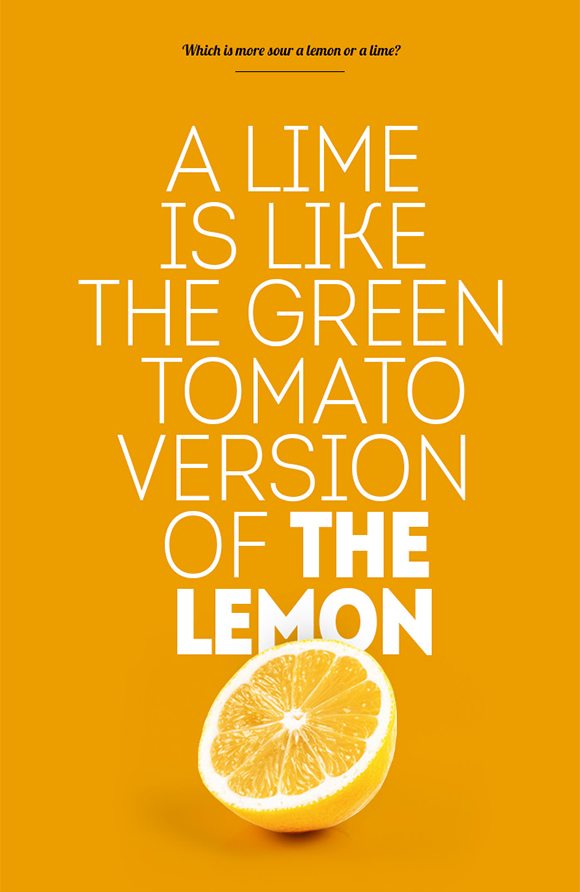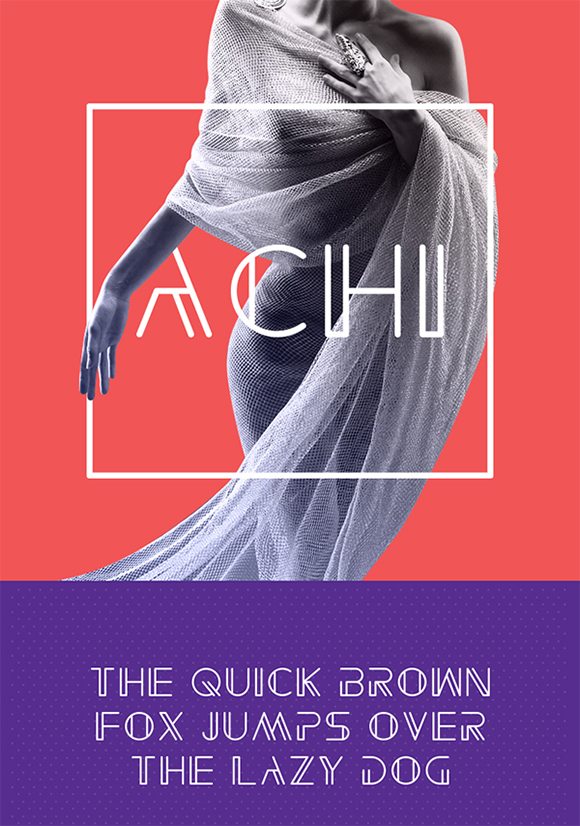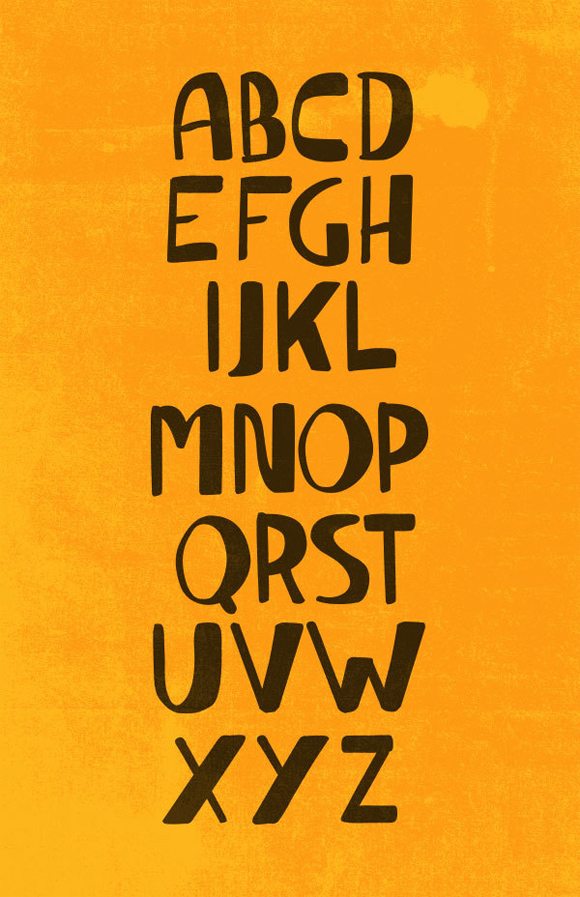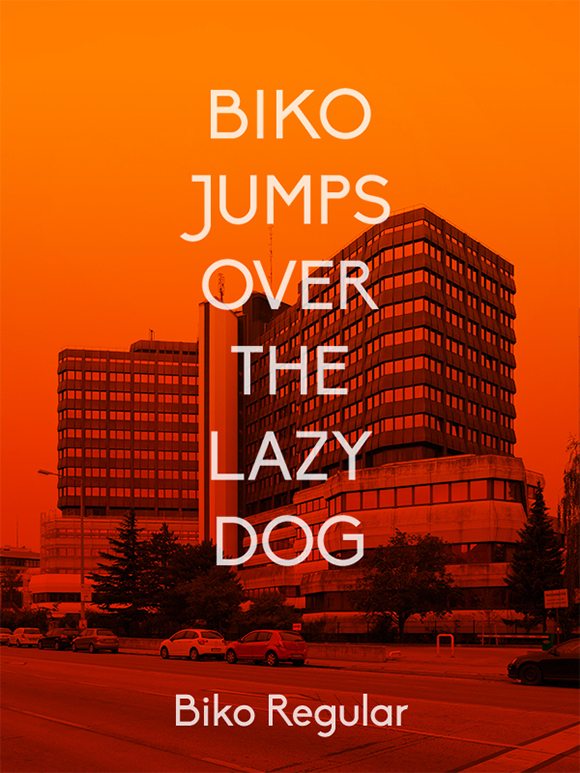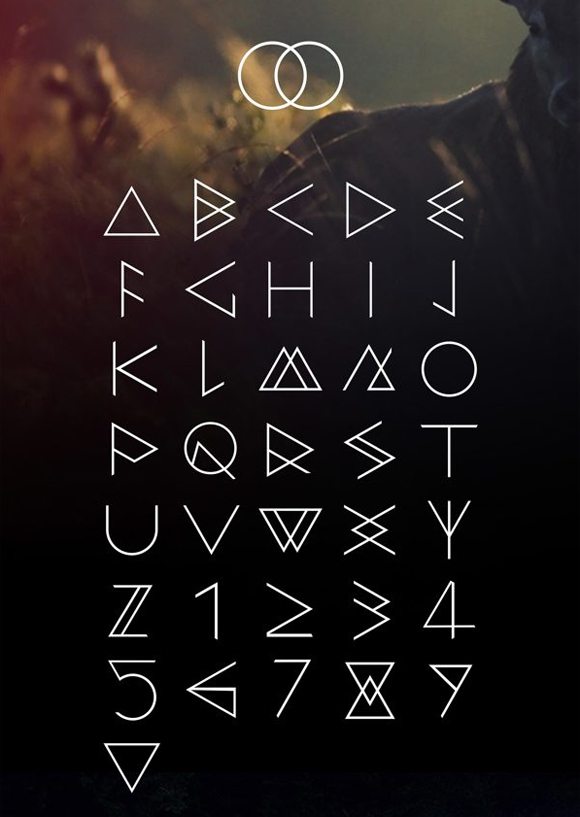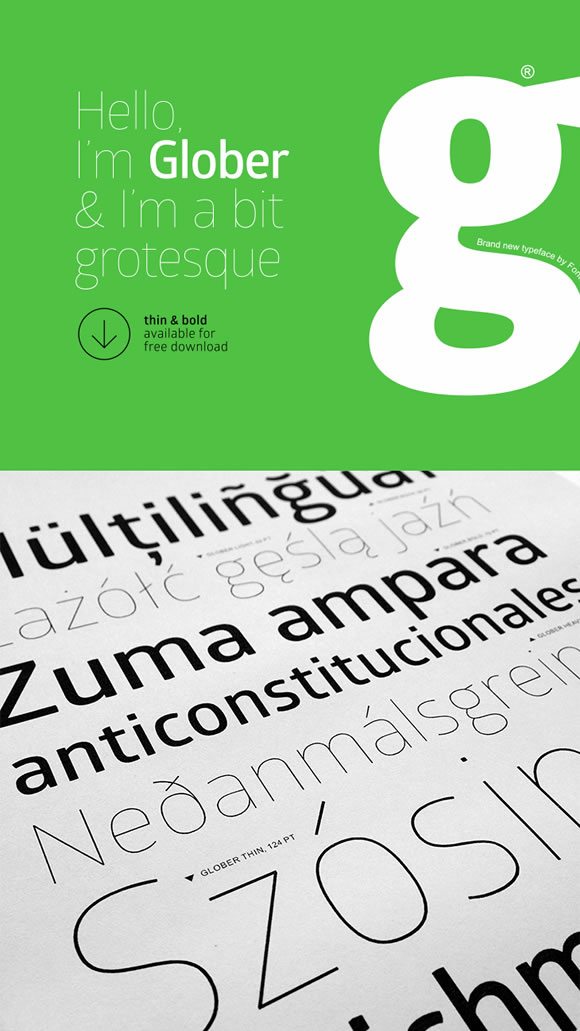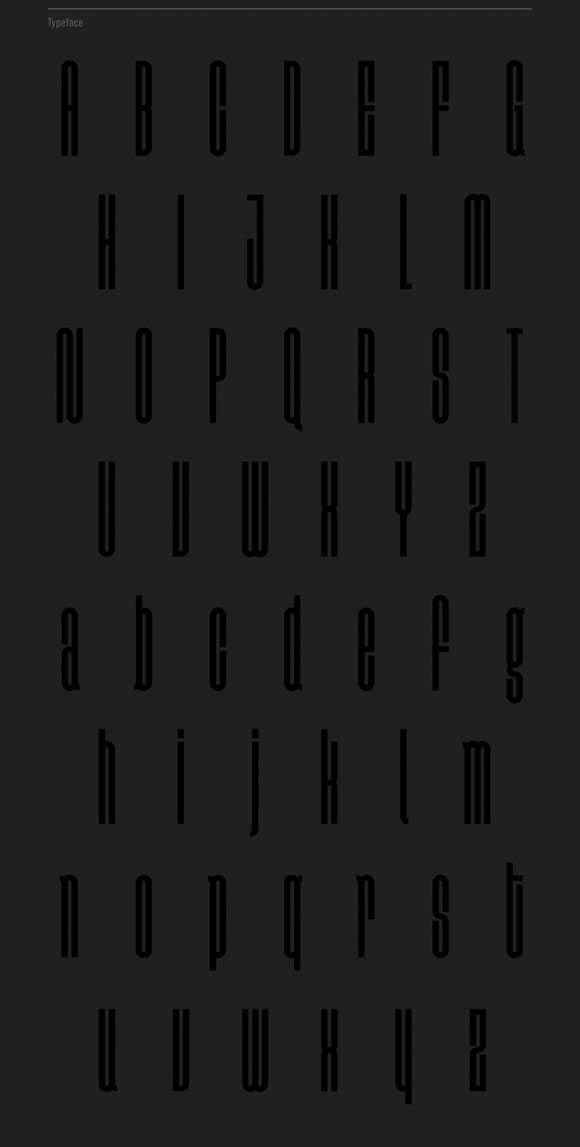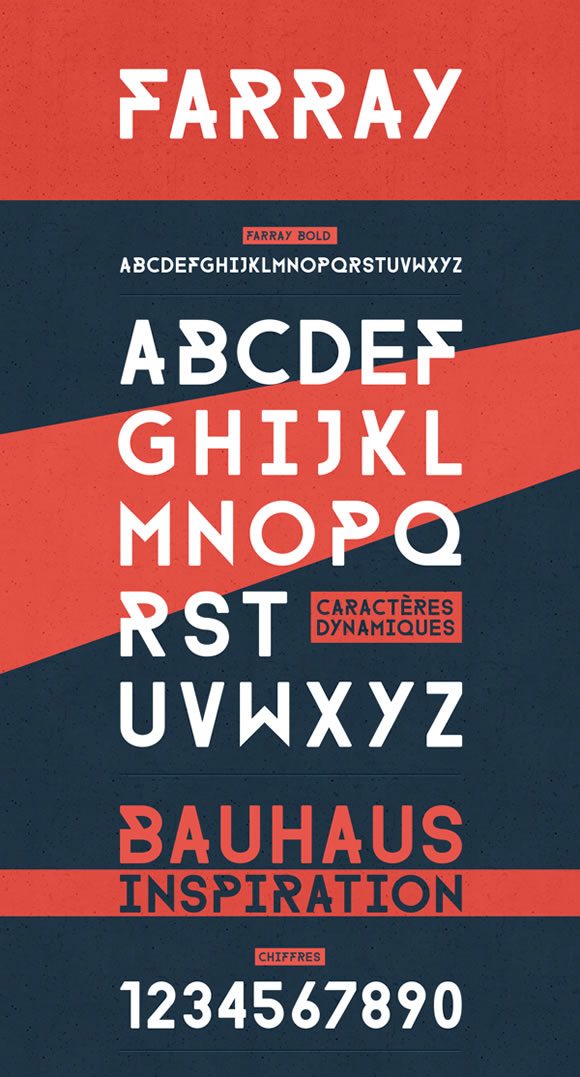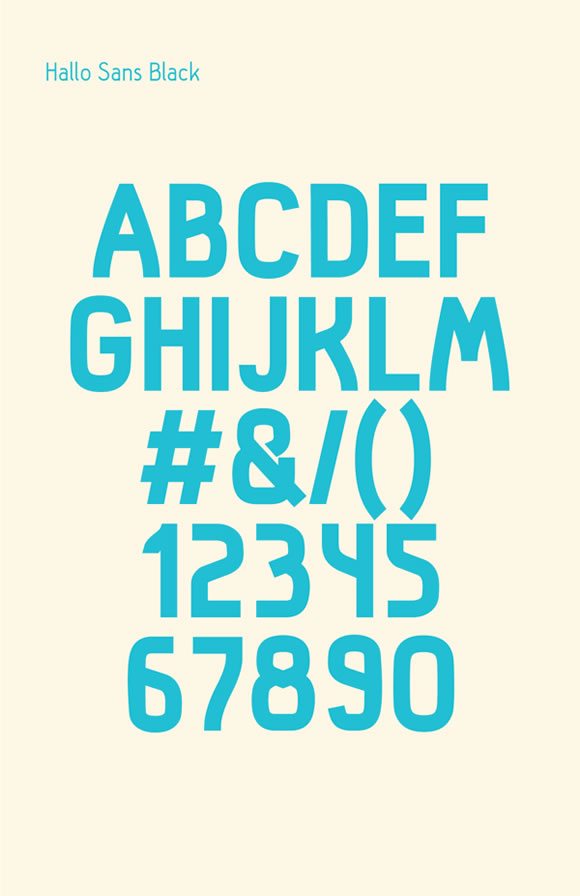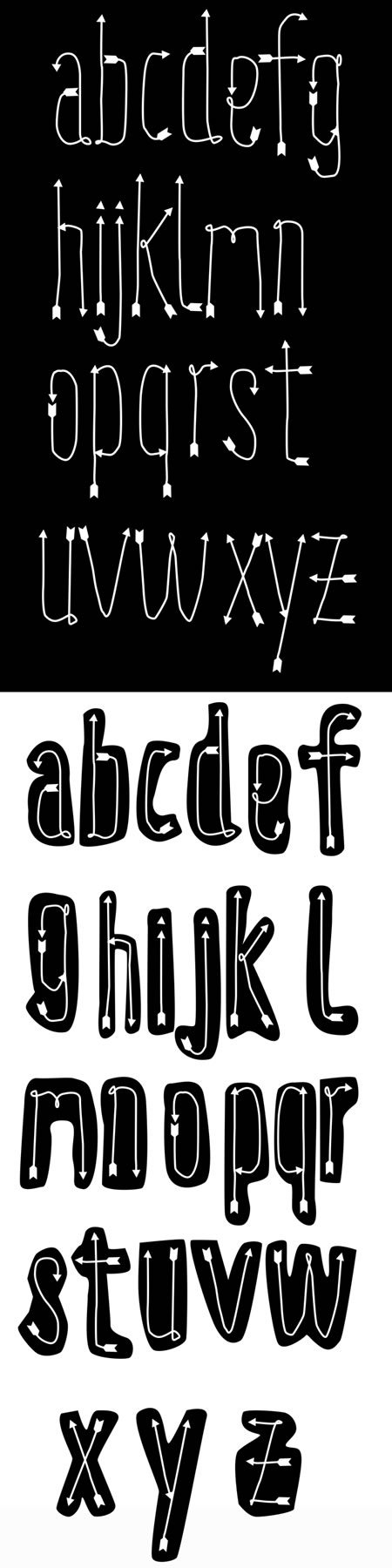
top 100 dei font gratuti del 2015 da avere assolutamente
per chiudere l’anno in bellezza  vi stiamo dando le migliori risorse del 2015 e non potevamo che cominciare dalla top ten dei font più usati e scaricati del 2015, alcuni li avrete già sicuramente visti e usati ma eccoveli tutti insieme. Non temete sono comunque stati divisi sotto una certa logica, quindi non faticherete a trovare quello che cercate!
la top ten dei migliori font:
Campton
Globar
Disclaimer
Simplifica
Aqua Grotesque
Farray
Hallo Sans
Tesla
Look Up
Mohave
font fini e leggeri
EXO
Aaargh
QUARZ 974 Light
Milano
Chelsea
Verano
Penelope Anne
Party at Gatsby’s
Before the Rain
Penna
Capsuula
Znikomit
Print Clearly
Adine Kirnberg
Raleway
Adequate
Windsong
Aleo
Venera
Attentica
Sequi
Font gemetrici
Walkway
MANIFESTO
Big John / Slim Joe – FREE Font
Moon – Free Font
Metrophobic
PIER FREE TYPEFACE
BUILDING
Moderne Sans
SIMPLIFICA